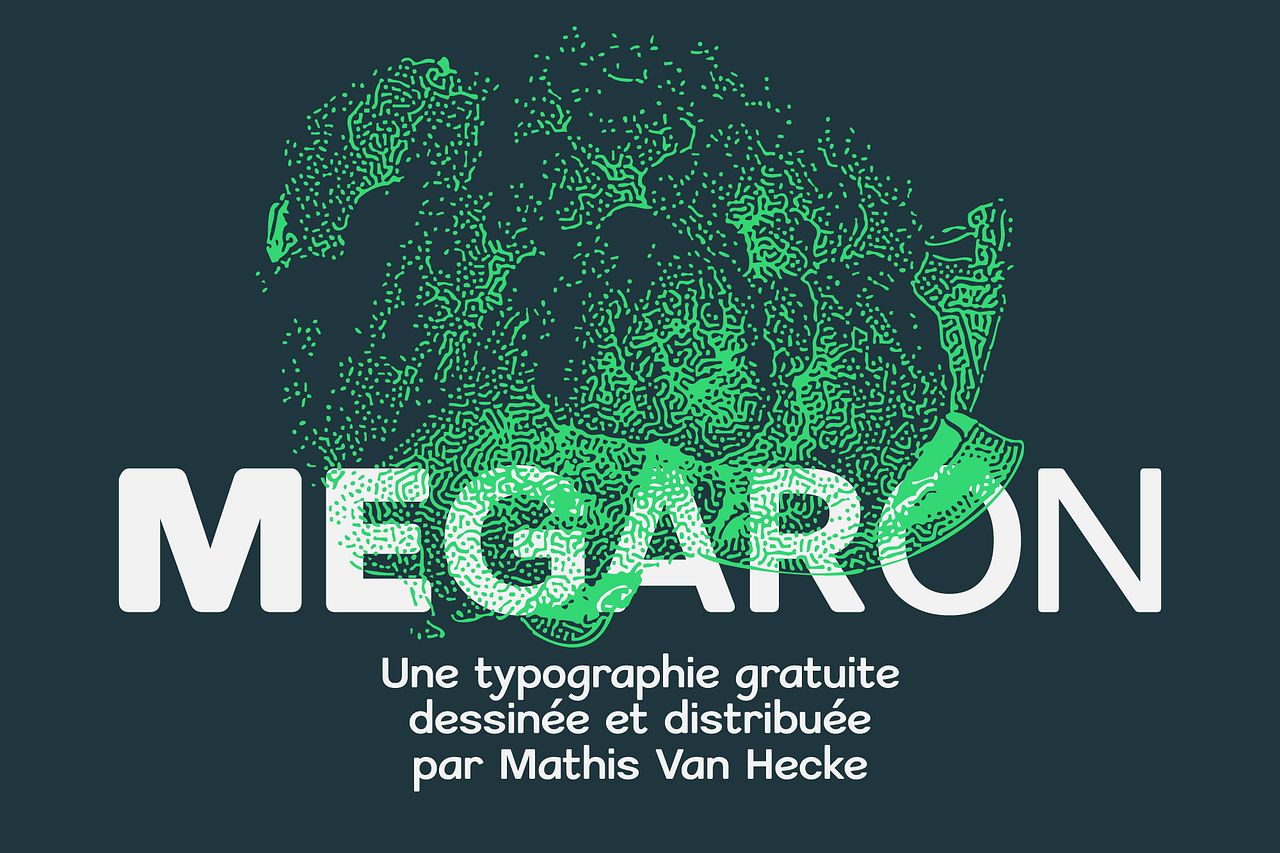
Megaron — typeface
Megaron est une police de caractère sans empattement inspirée des linéales. Elle est destinée à la signalétique de la micro-ferme pédagogique des Cols Verts à Rennes. Cette typographie a été pensée de manière à être la plus lisible et claire possible. Elle existe en 4 graisses, Regular, Medium, Semibold et Bold.